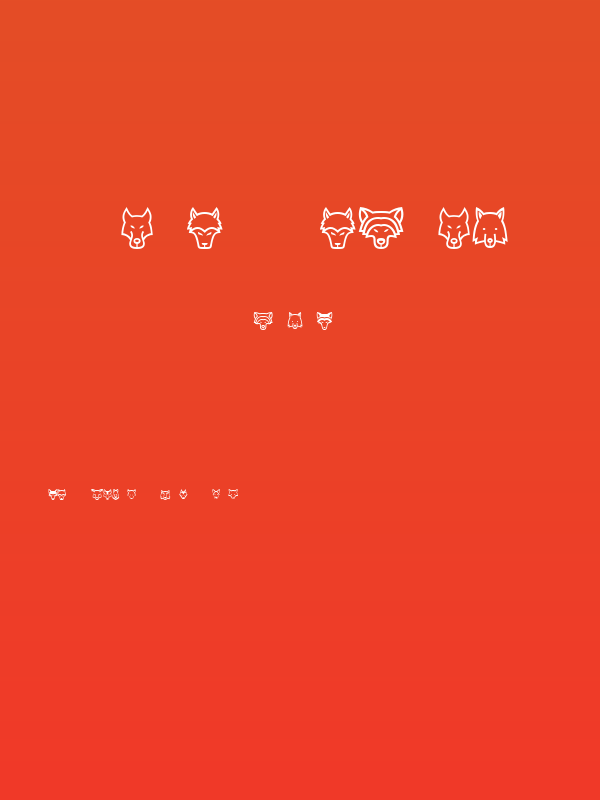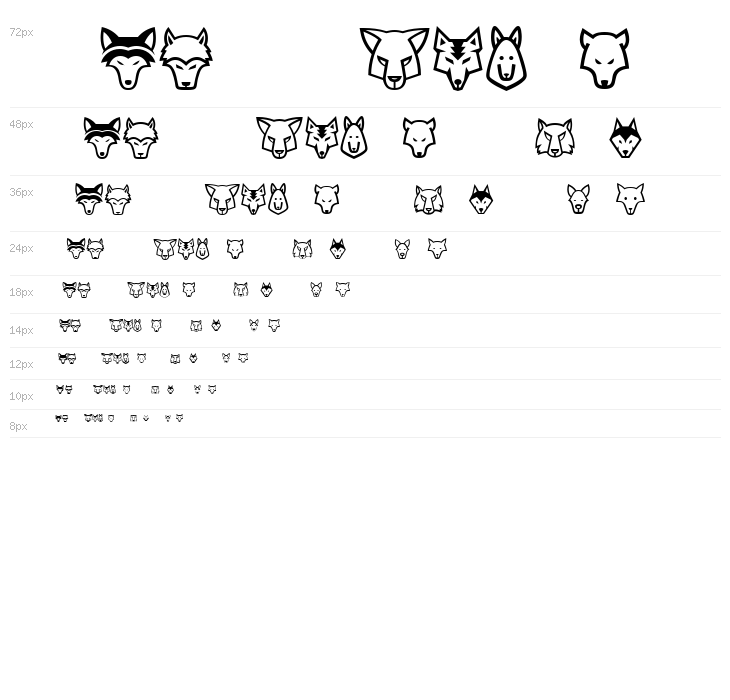
Wolves Regular Font
| Stile generale | Decorative, Playful, Thematic |
| Caso d'uso | Logos, Headlines, Themed graphics, Posters |
| Progetti proposti | Children’s books, animal-themed posters, educational materials, branding for pet or wildlife organizations, playful invitations. |